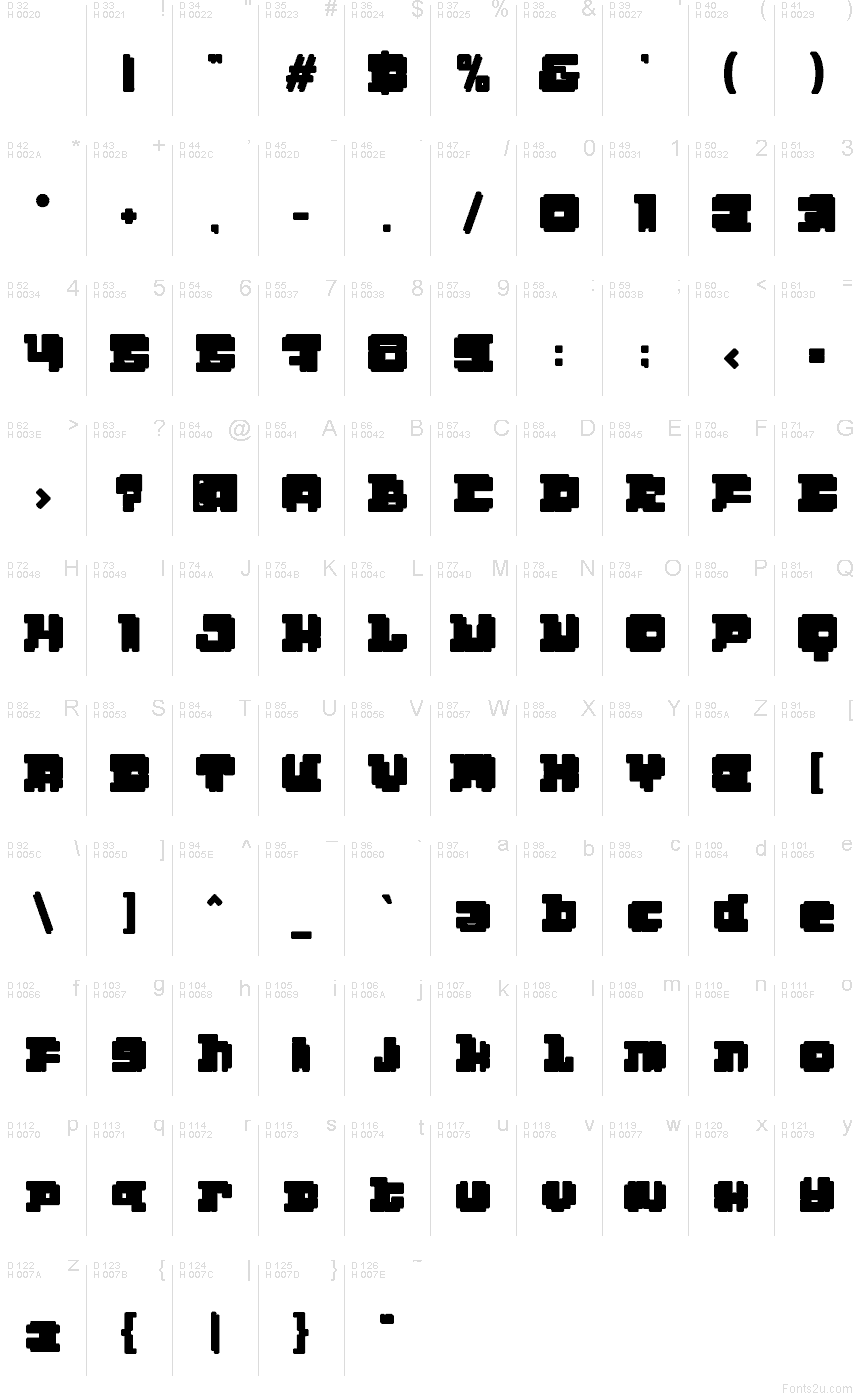
Techno Wave One od Putracetol Studio je bezplatné, futuristické bezpatkové písmo typu display postavené na zúžených obdélníkových tvarech a opakujících se vrstvách, díky nimž každé písmeno působí dojmem, že je poskládané na sobě a vibruje. Tento vrstvený efekt dodává písmu pulzující rytmus, takže design působí spíše jako kompaktní signál než běžný font ve stylu sci-fi.
Skvěle funguje v herních titulech, grafice pro streamery, letácích, promo akcích aplikací i na plakátech, kde jeho vrstvená silueta vizuálně zaujme na první pohled. Konstrukce s opakujícím se stínem navíc dodává krátkým popiskům, obalům hudebních alb i technologickému brandingu syntetický arkádový nádech bez nutnosti dalších efektů.